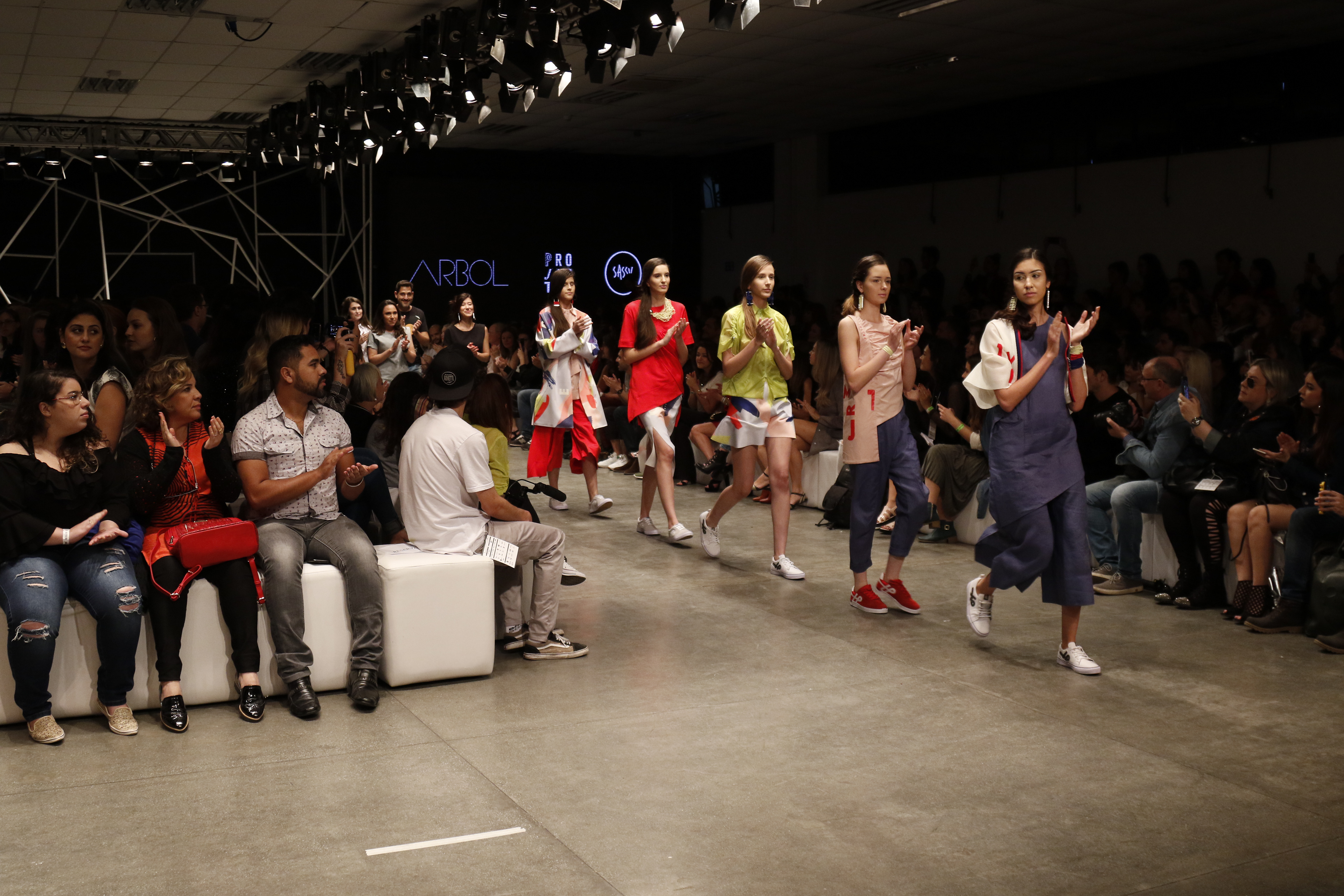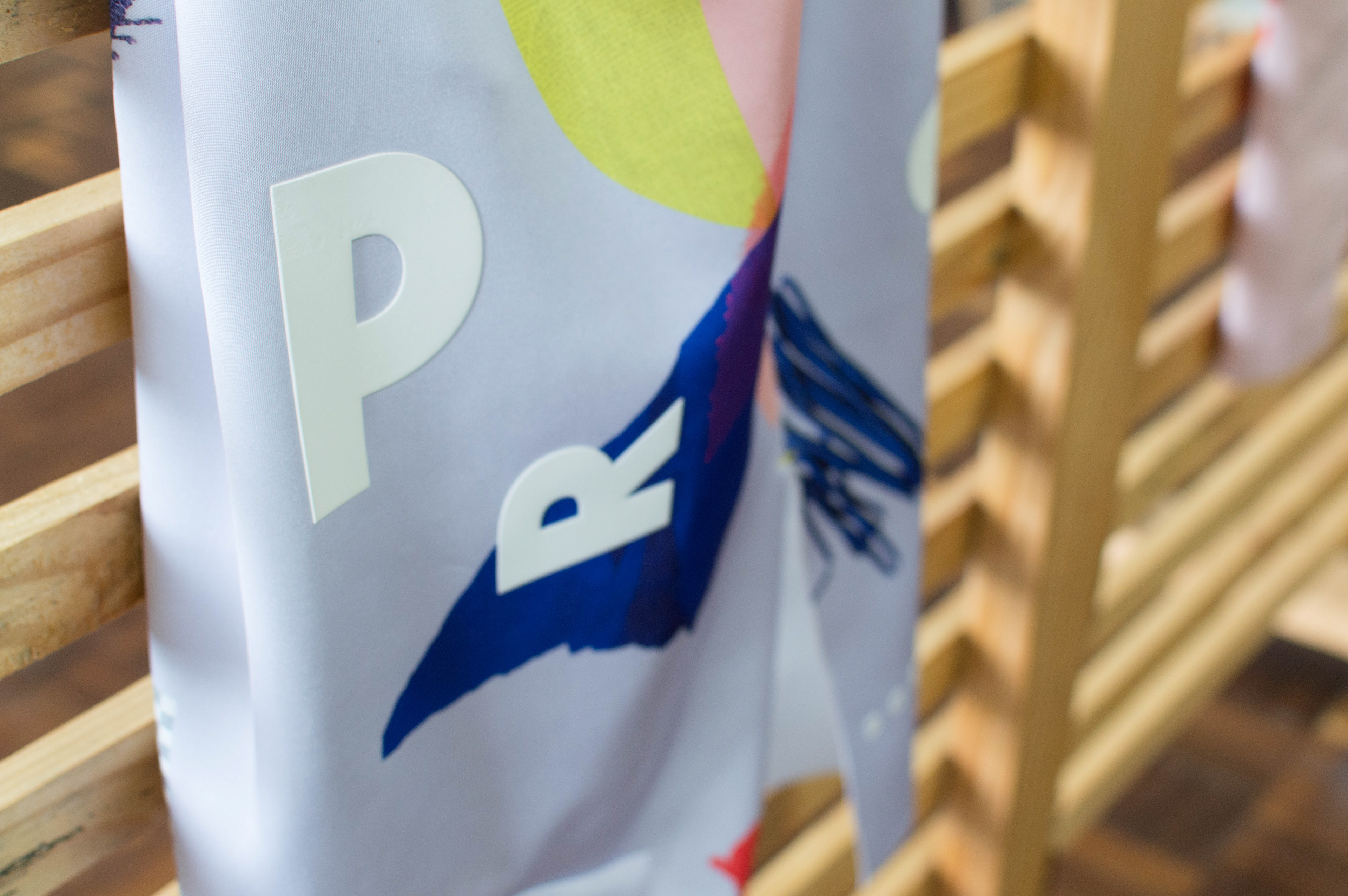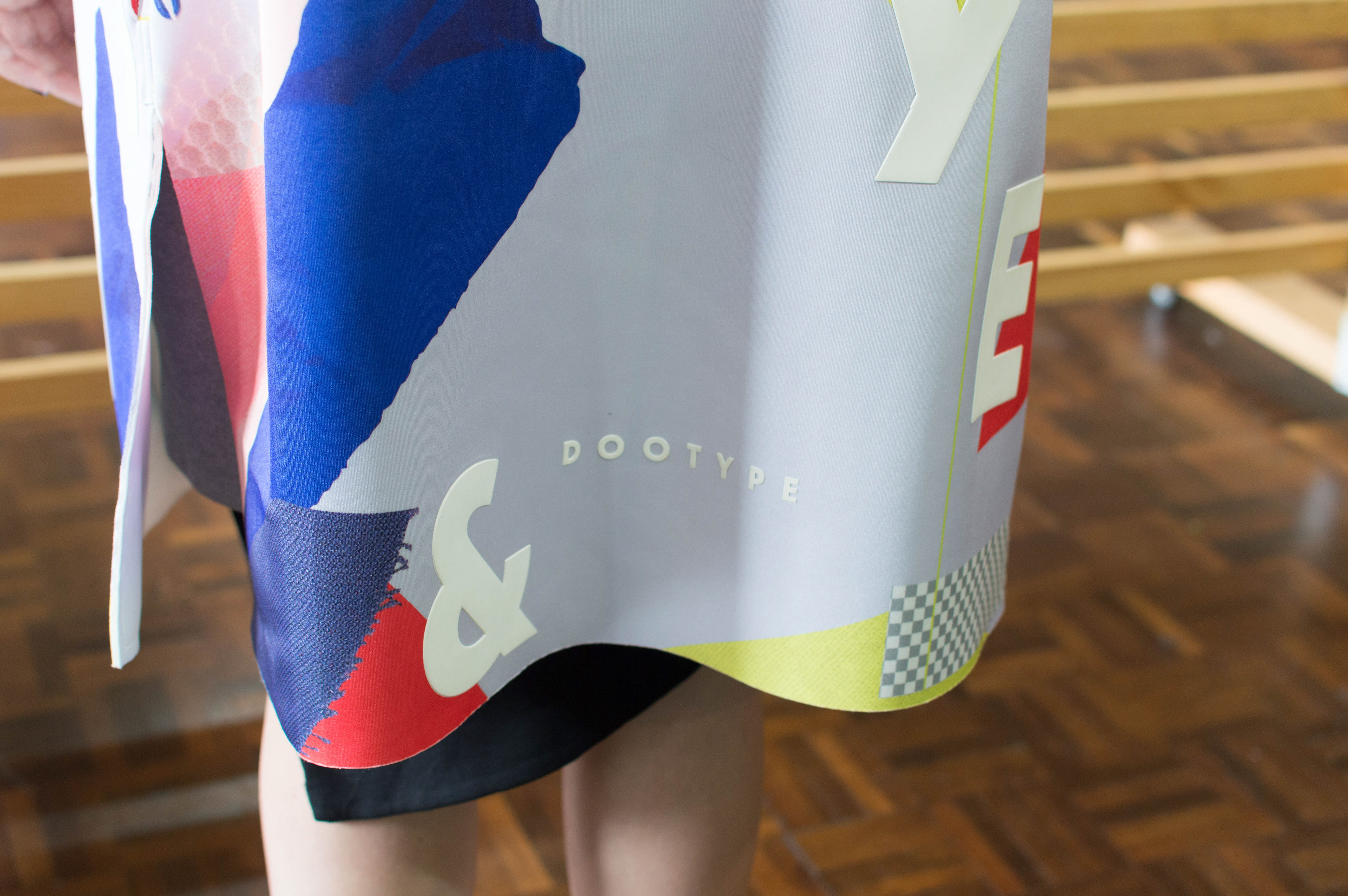
TYPE IN USE - dT JAKOB
Projeto Zero Um
Conheça o Projeto Zero Um (Prjt01), liderado pelas designers Patrícia Hirozawa e Vanessa Gabardo.
Para sua mais nova coleção, exibida no ID Fashion, o duo utilizou as formas geométricas da nossa recém lançada dT Jakob.
Ficamos muito felizes com o resultado final e também com a forma não usual da utilização da tipografia.